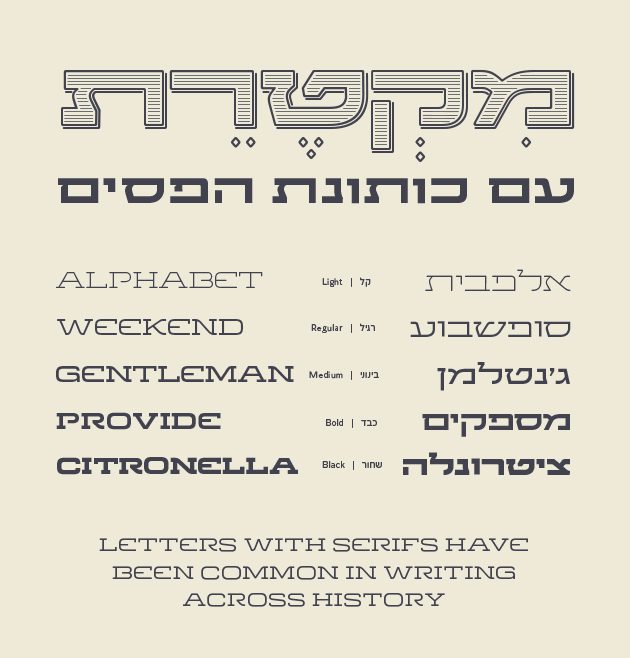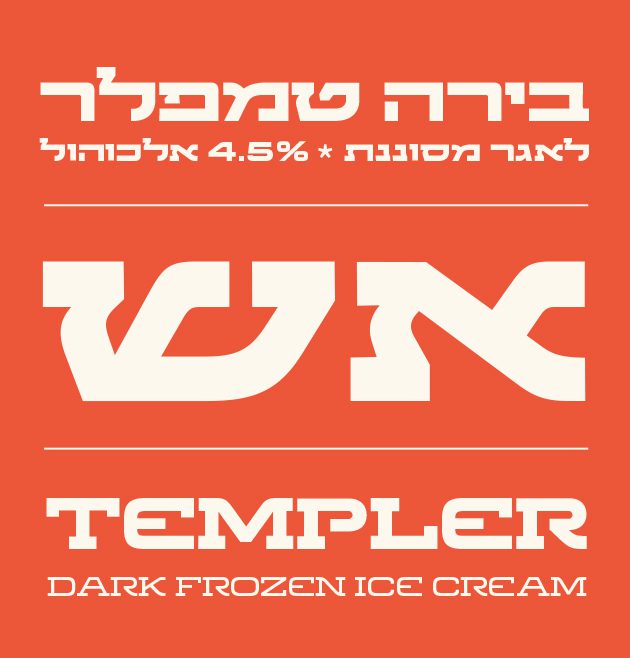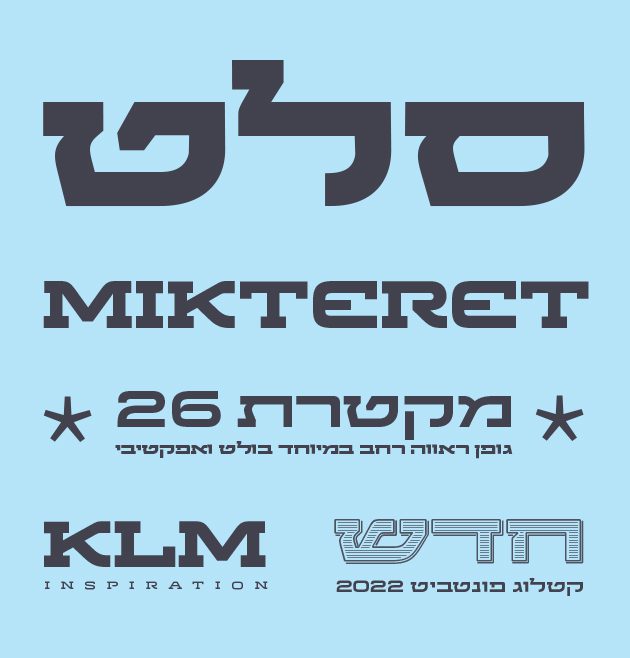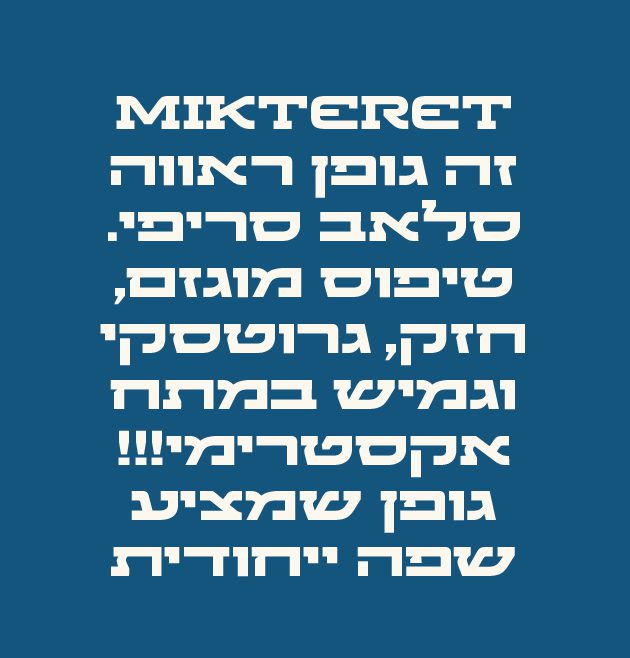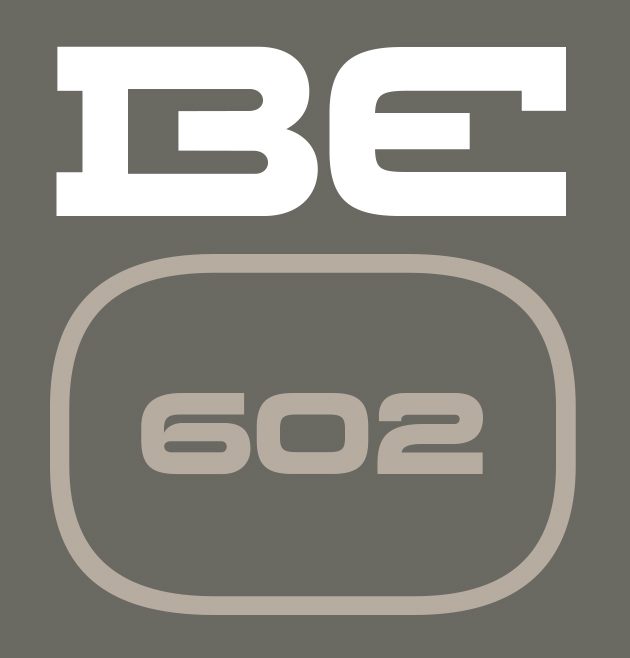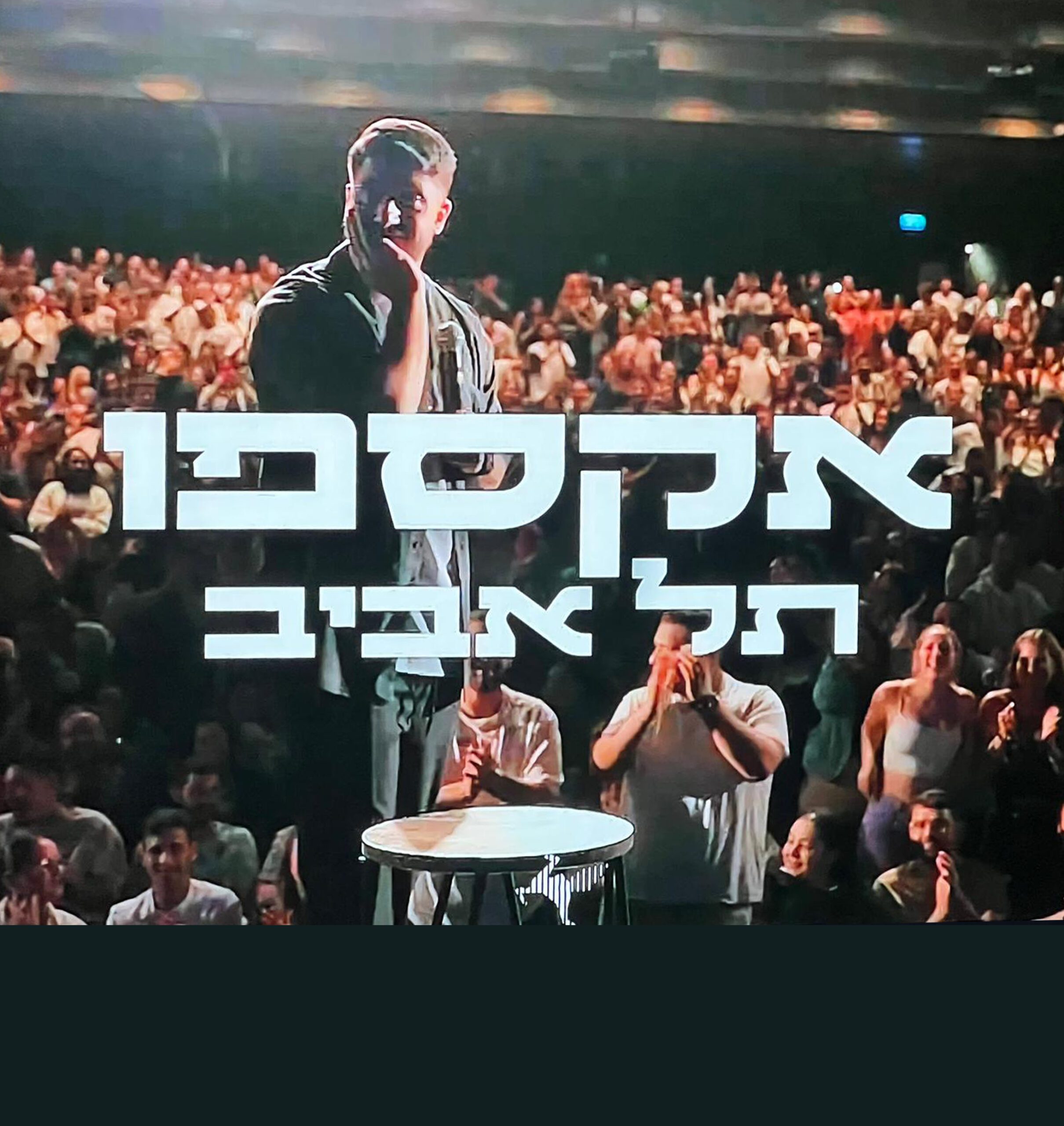
מקטרת
מקטרת / Fb Mikteret
• שם הגופן:מקטרת
• מעצב הגופן:נדב עזרא
• סגנון:סלאב סריף
• מאפיינים: דקיק קל רגיל בינוני כבד פסים
• תכונות: אוונגרדי מודרני מרובע קשיח
סיפור הגופן:
מקטרת הינו גופן ראווה סלאב סריפי המאופיין כטיפוס מוגזם, חזק וגרוטסקי עם גמישות במתח אקסטרימי! גופן שמציע שפה ייחודית מלאה בכריזמה. למעשה בחנתי את הגבול הרחוק ביותר של אות עברית רחבה, כך שעדיין יצליח להחזיק טקסט באופן קריא וברור. לשם כך בניתי את האות עם הרבה כיפופים אותם לקחתי מהמבנה הקלאסי של האות העברית ועיצבתי להם תרגום עדכני ומדליק ובכך מצליח הגופן לפרוץ מחוץ לריבועיות האופיינית לו כגופן רחב. בסופו של דבר התגבשה האות למשפחת גופנים דו-לשונית ומרובת משקלים הכוללת גם משקל פסים מיוחד שמתאים לעיצוב לוגו.